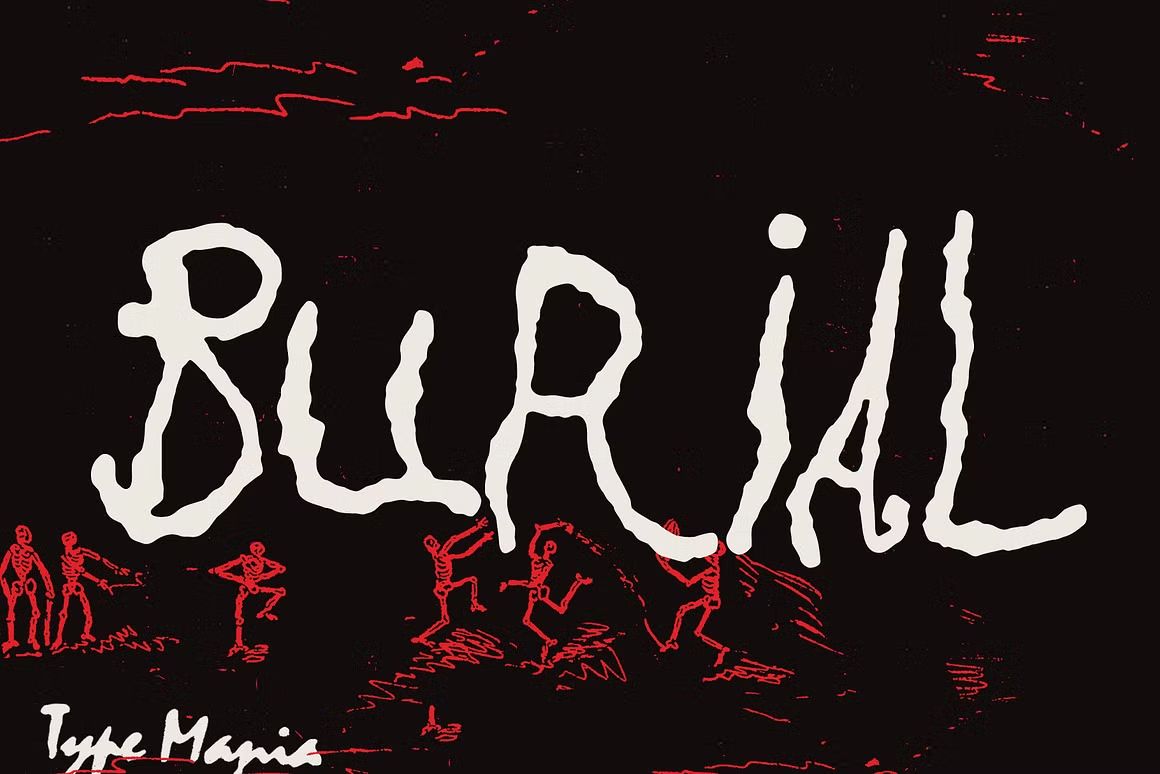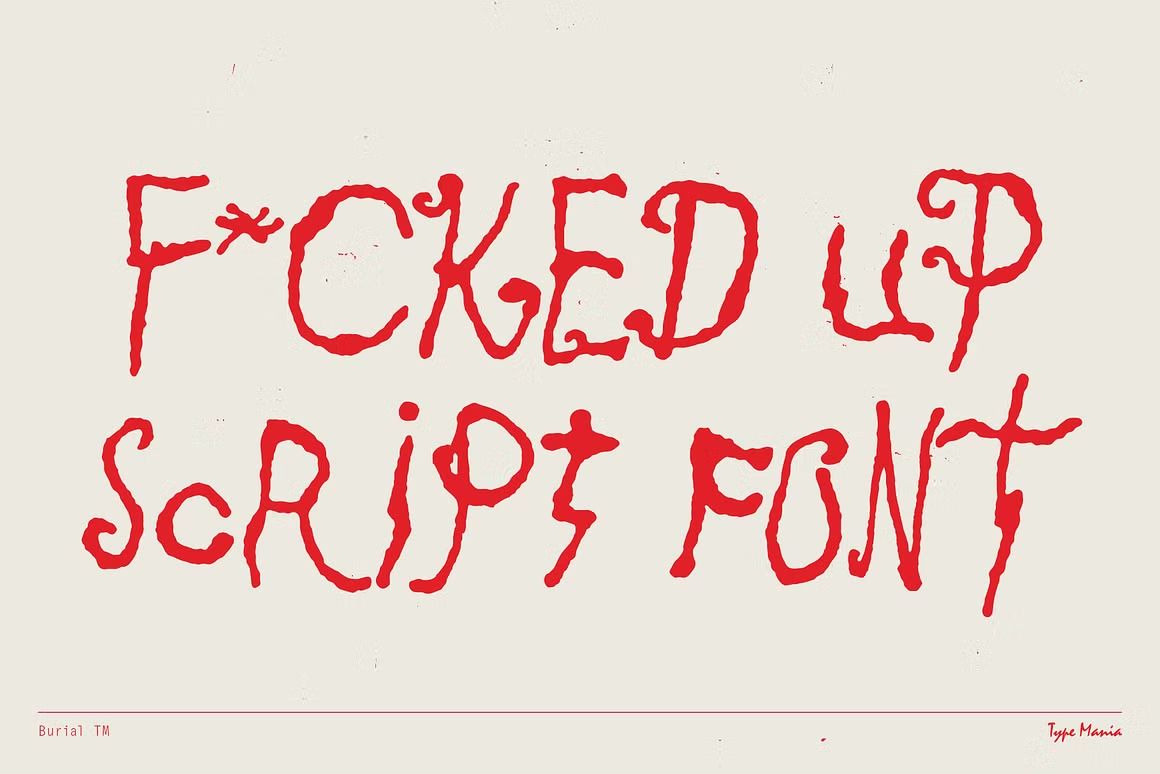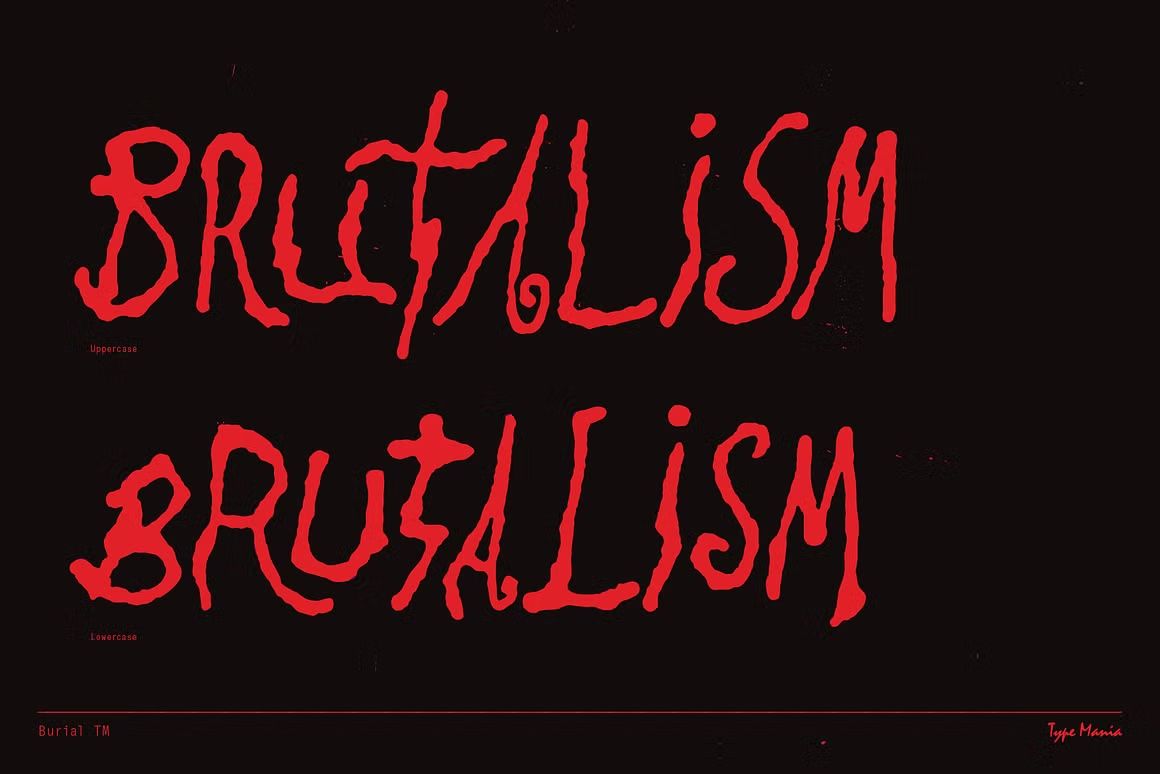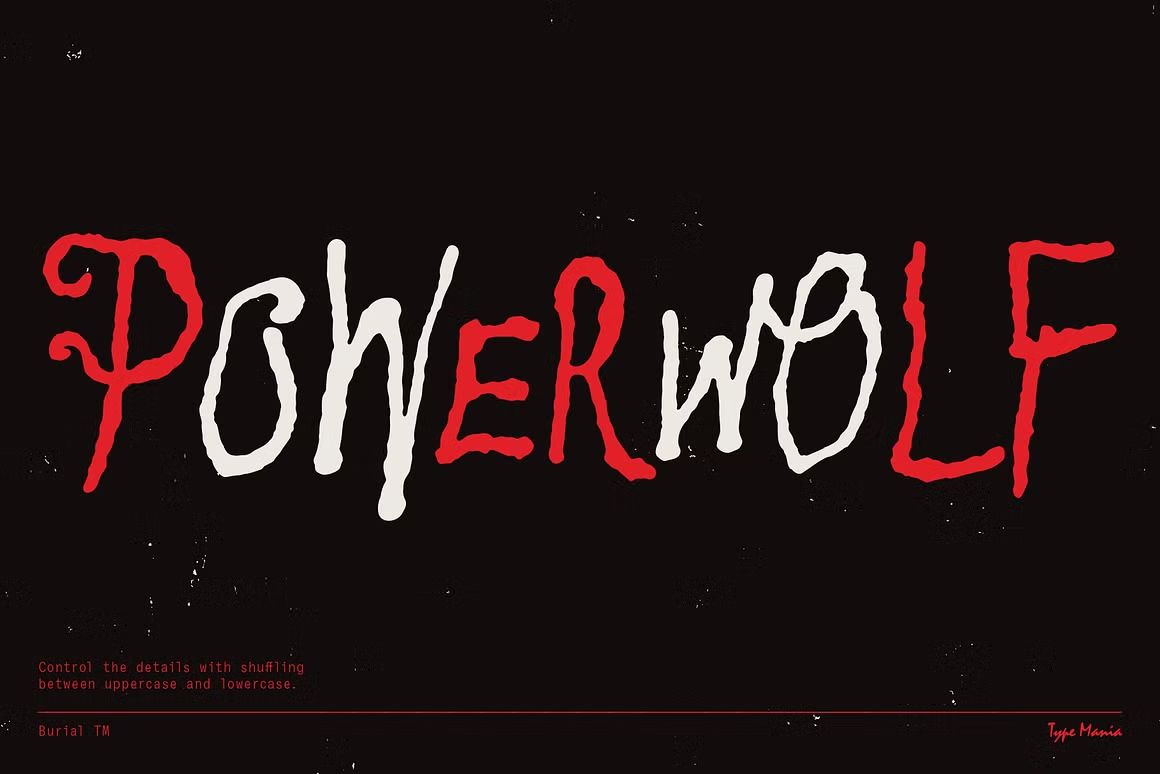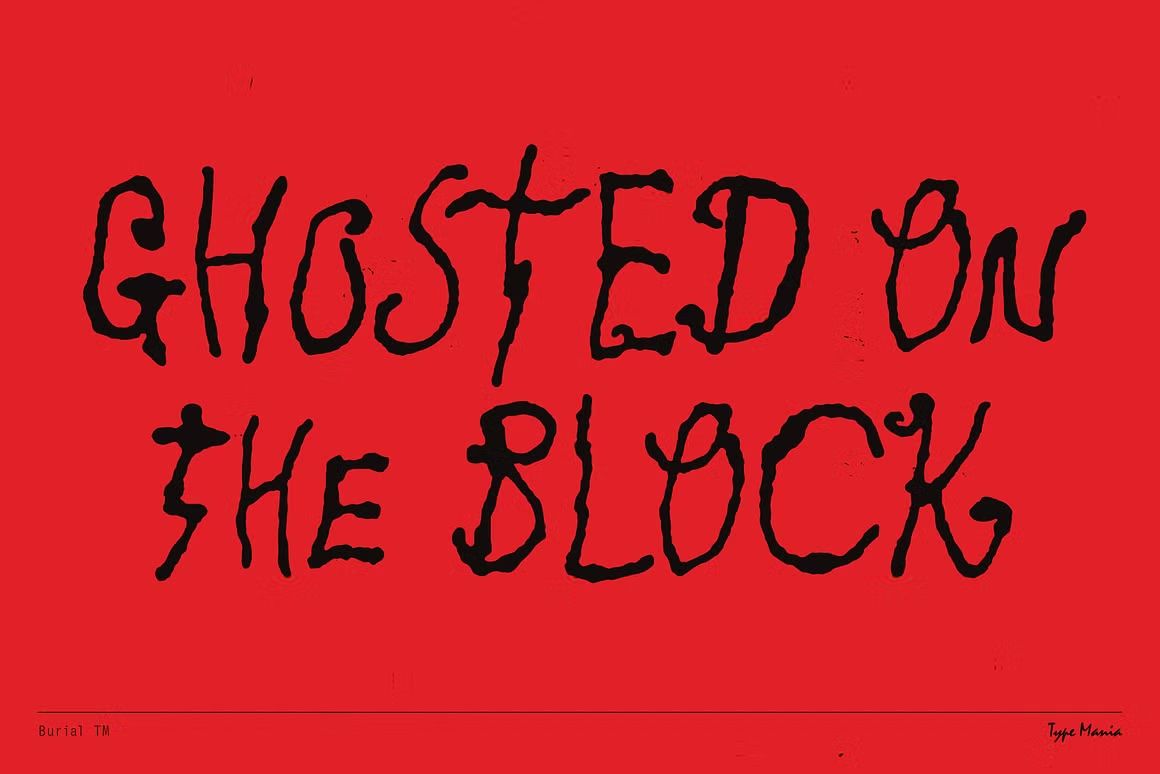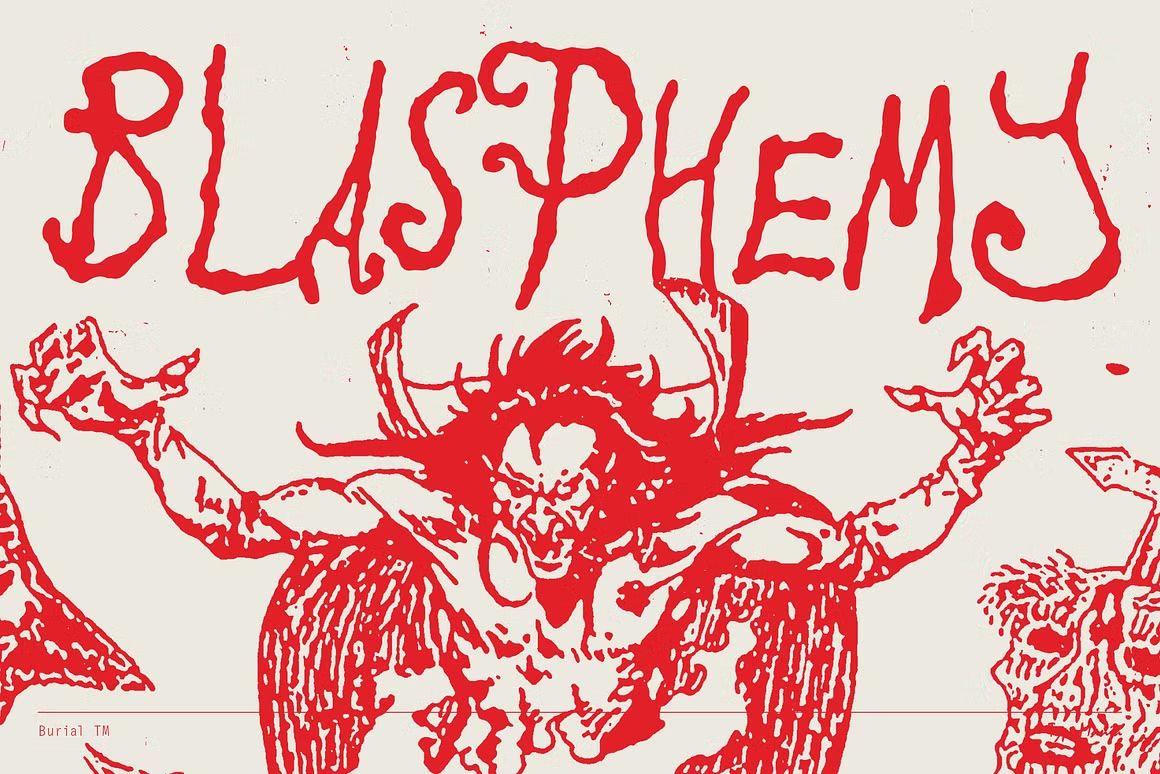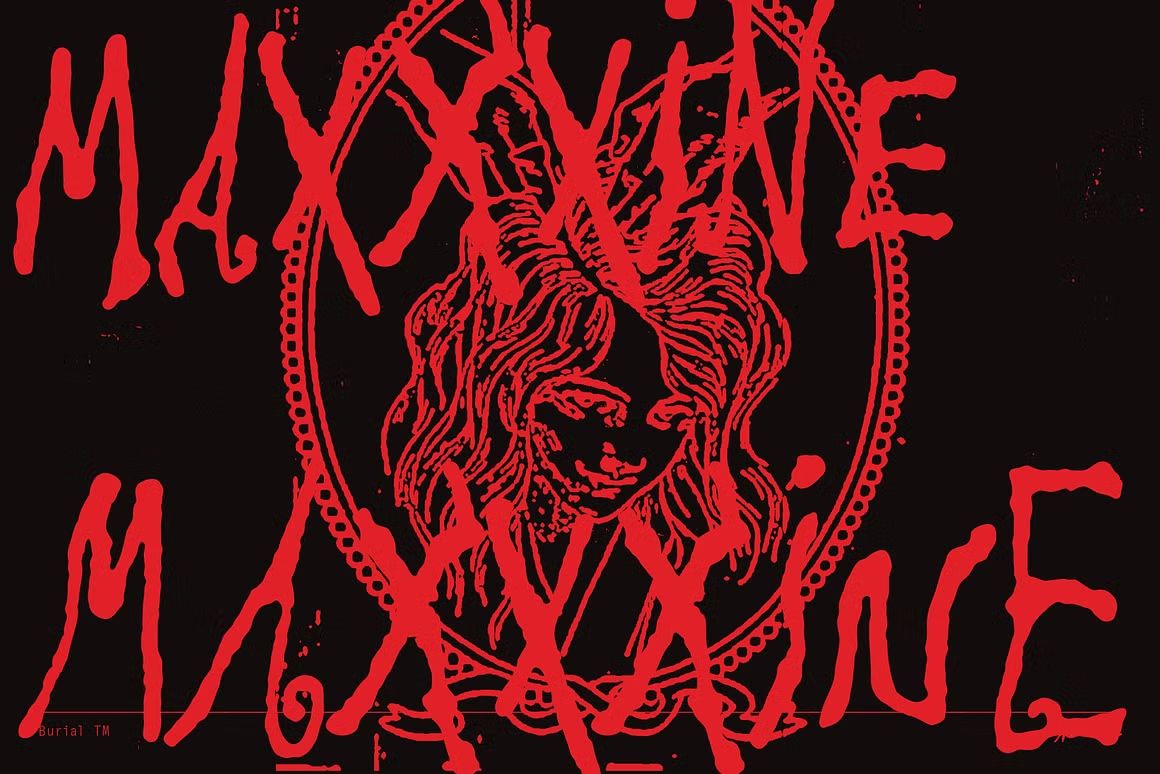
Burial TM – Handwritten Font
Burial TM adalah font handwritten bergaya ekspresif dan bold, cocok untuk desain kreatif dan konten edgy. Format OTF/TTF/WOFF, siap digunakan.
Burial TM adalah font handwritten dengan gaya ekspresif dan bold, menghadirkan tampilan yang mentah, artistik, dan penuh karakter. Cocok untuk desain alternatif seperti poster musik, cover album, branding kreatif, dan konten media sosial yang edgy dan berani. Gaya tulisannya yang tidak rapi namun dinamis memberikan kesan emosional dan otentik dalam setiap karya.
• Handwritten font dengan gaya kasar dan ekspresif
• Ideal untuk desain alternatif, musik, dan konten edgy
• Termasuk huruf besar, kecil, angka, simbol, dan ligatur